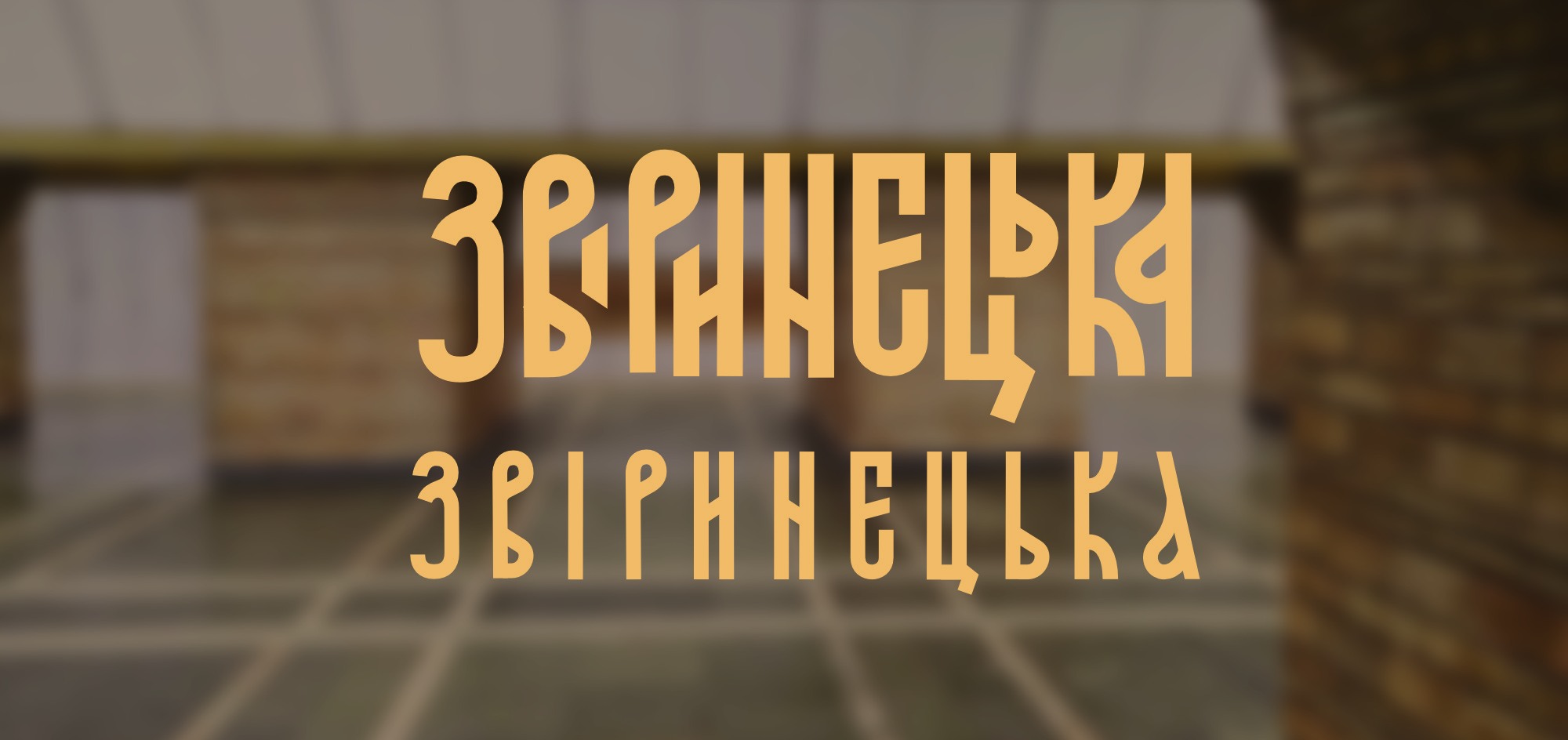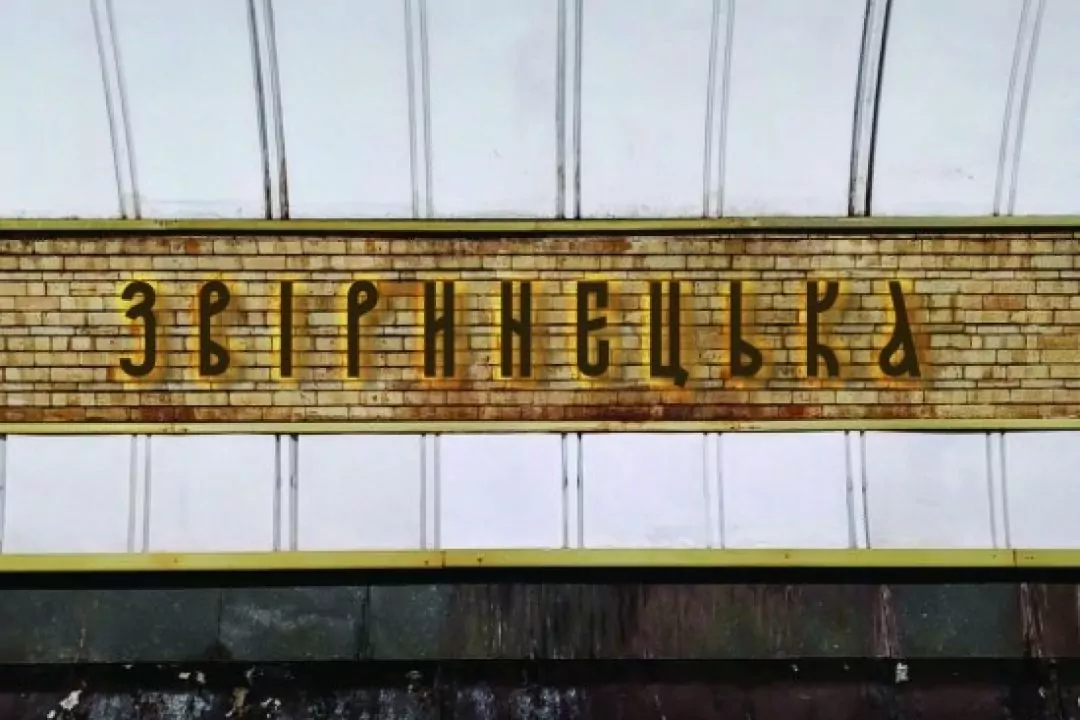
Киевский дизайнер разработал шрифт для названия станции метро «Зверинецкая»
Дизайнер Богдан Гдаль показал один из вариантов шрифта нового названия станции метро «Дружбы народов». 18 мая Киевсовет переименовал ее в «Зверинецкую».
Об этом Богдан сообщил на своей фейсбук-странице.
Первый вариант шрифта дизайнер создал, вдохновившись буквами Саши Комьяхова, которые тот делал на основе надписей Трапезной церкви Киево-Печерской Лавры.
Богдана зацепил этот арт-проект. Дизайнер почувствовал, что он подходит под Зверинецкую, объяснил автор изданию «Хмарочос».
Дизайнер планирует, что разработает еще один вариант шрифта.
Кроме того, Богдан разработал шрифт для новой надписи на станции метро «Почайна». Известно, что по просьбе архитектора Тамары Целиковской, шрифт должен был повторять имеющийся на станции «Печерская».
Ранее мы писали, что Гдаль создал шрифт для названия станции киевского метро «Площадь Украинских Героев» (бывшая Площадь Льва Толстого). Украинский дух в буквах Гдаль передал с помощью 2 составляющих: оригинальных исторических форм некоторых букв и стиля с начала 20 века эпохи Нарбута и Кричевского.